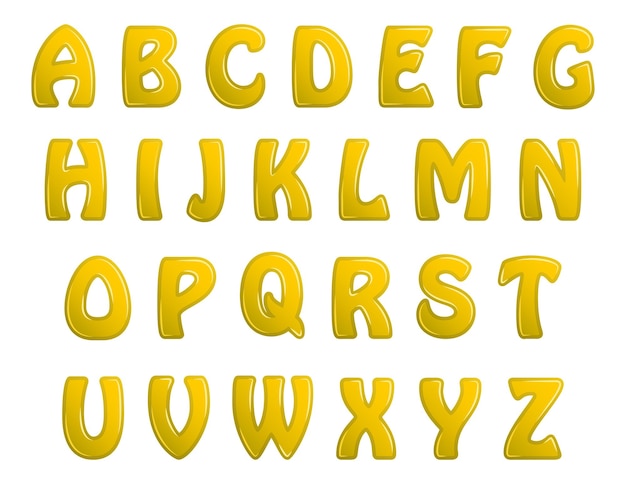
d Желтый пластиковый воздушный шар алфавит символы и цифры блестящие раздутые шрифт yk вектор abc изолирован
D Желтый пластиковый воздушный шар алфавит символы и цифры блестящие раздутые шрифт yk вектор abc изолирован